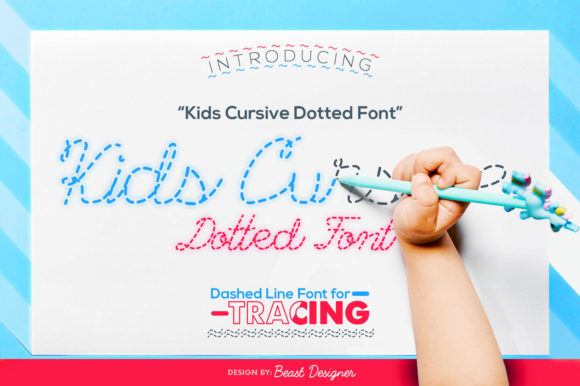
Kids Cursive Dotted
Kids Cursive Dotted – O Font de Caneta Curva com Pontilhado que Vai Encantar Seus Pequenos
Se você está em busca do font perfeito para trabalhar com crianças em idade pré-escolar, Kids Cursive Dotted é a escolha certa. Este tipo de letra, desenhada com pontilhado, combina diversão e praticidade, permitindo que os pequenos pratiquem a escrita de forma interativa e visualmente estimulante.
Por que o Kids Cursive Dotted é Ideal para Planilhas de Traçado?
- Fácil de Seguir – as linhas pontilhadas guiam os dedos das crianças, facilitando a coordenação motora fina.
- Estética Atraente – a cursiva suave e o design dashes criam um visual amigável e elegante.
- Versatilidade – pode ser usada em cartazes educativos, folhetos, convites infantis e muito mais.
Conclusão: Seu Próximo Font Favorito
Ao adicionar o Kids Cursive Dotted ao seu portfólio, você oferece uma ferramenta de aprendizado que combina diversão e eficácia. Experimente em projetos escolares, kits de artesanato ou até mesmo em branding de marcas voltadas para o público infantil. Com sua estética única e funcionalidade comprovada, este font rapidamente se tornará seu favorito para qualquer criação que envolva crianças.